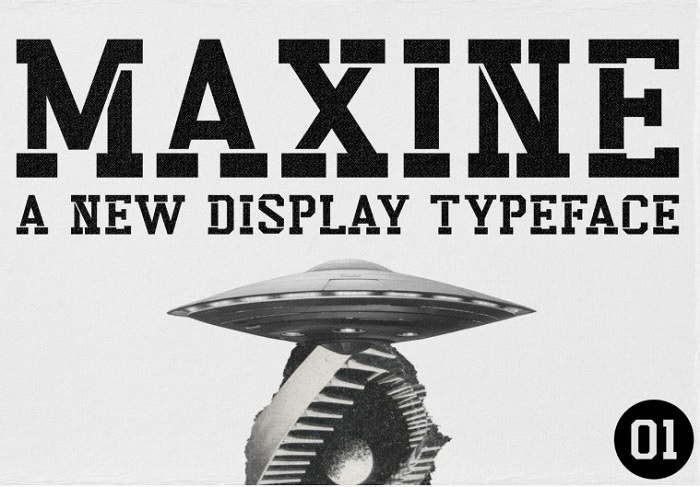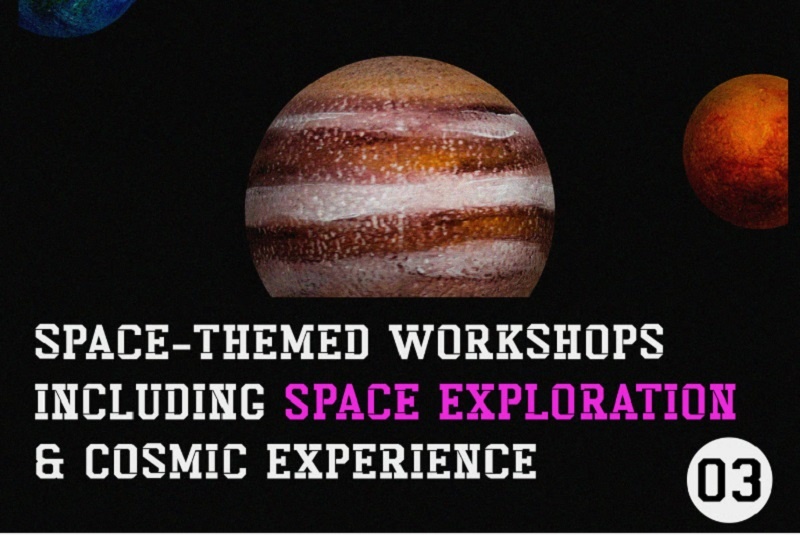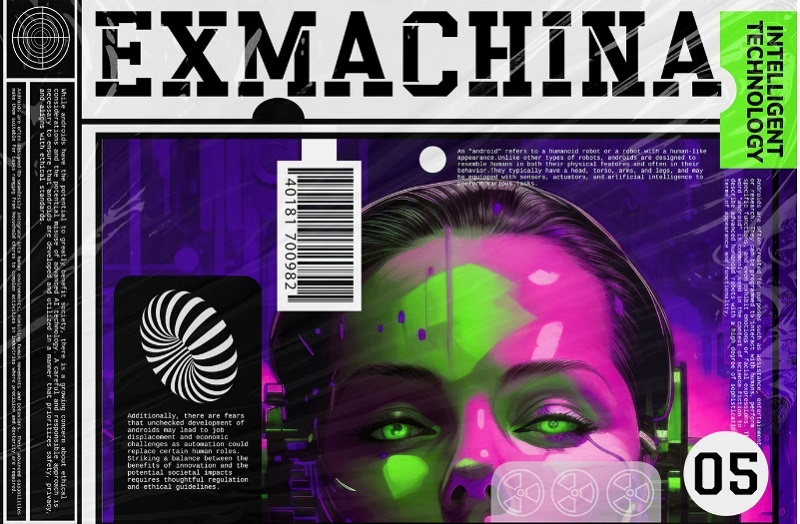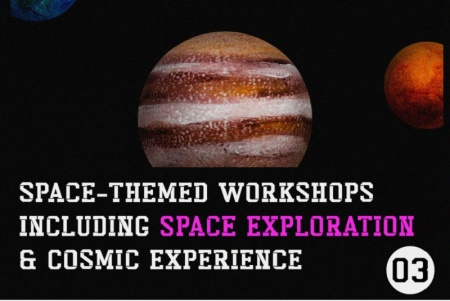
دانلود فونت انگلیسی با استایل آینده نگر و مدرن Maxine
فونت انگلیسی با استایل آینده نگر و مدرن Maxine
دانلود فونت انگلیسی با استایل آینده نگر و مدرن Maxine. فونت Maxine Display یک فونت نمایشی آینده‌ نگر با طراحی مدرن است که برای پروژه‌ هایی با حال‌ و هوای تکنولوژی، برند های نوآور، طراحی رابط کاربری یا گرافیک‌ های مفهومی کاربرد دارد. این فونت انگلیسی آینده‌ نگر، حسی از آینده و نوآوری را به طراحی شما اضافه می‌ کند. چه برای ساخت یک پوستر دیجیتال، چه طراحی لوگو برای یک برند فناوری یا در حال ساخت رابط کاربری اپلیکیشن باشید، فونت Maxine می‌ تواند جلوه‌ ای حرفه‌ای و آینده‌ محور به پروژه‌ تان بدهد.
فونت انگلیسی آینده‌نگر برای طراحی‌های دیجیتال Maxine
بهترین فونت نمایشی با استایل futuristic برای پروژه‌ های خلاقانه
ویژگی های فونت انگلیسی با استایل آینده نگر و مدرن Maxine
✅ مناسب برای طراحی هایی ب حال‌ و هوای تکنولوژی، فضا، استارتاپ و آینده